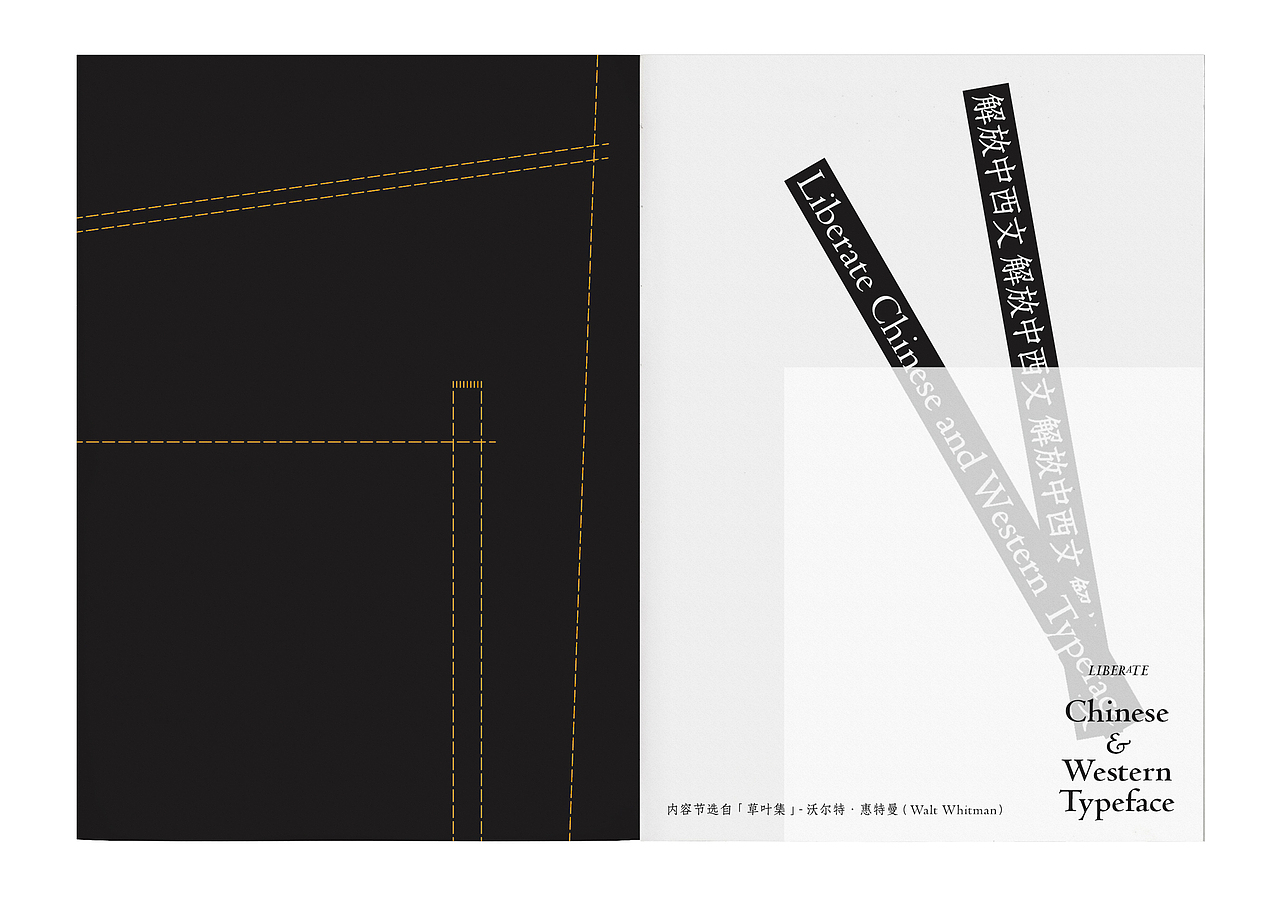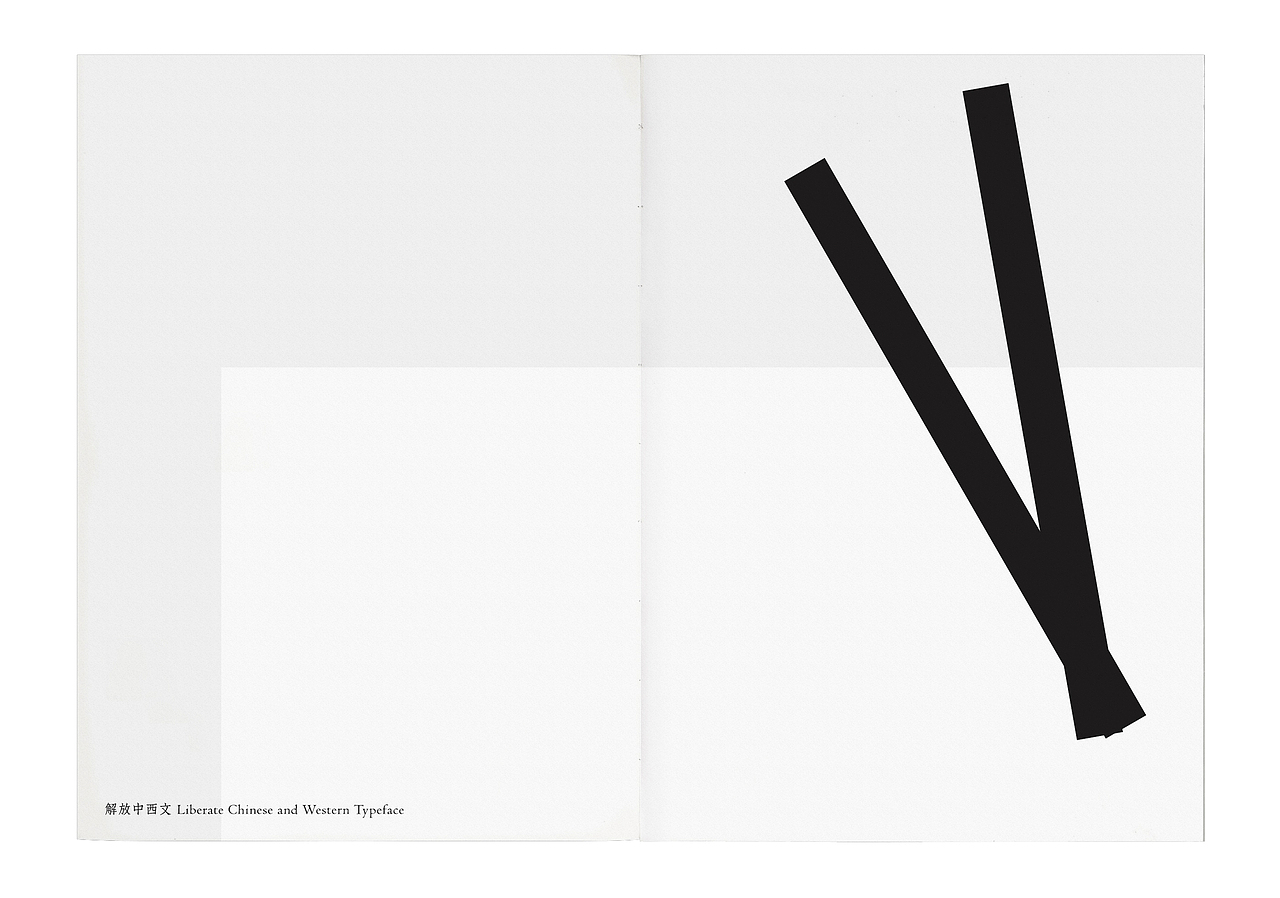
解放中西文 Liberate Chinese & Western Typeface
《解放中西文 Liberate Chinese & Western Typeface》是一本探讨中西文搭配风格同化问题的设计作品,又是一本观察、感受和探讨生活的设计作品。
创作以“中西文搭配风格同化是否在某种程度上会磨灭字体个性”为主题,向大家提出问题,同时引发出对社会与生活的思考。
对此作品有以下几点说明:
一、创作赋予了作品轻松、诙谐的氛围;
二、作品内容节选自沃尔特·惠特曼 ( Walt Whitman ) 的《草叶集》,仅做展示字体用。